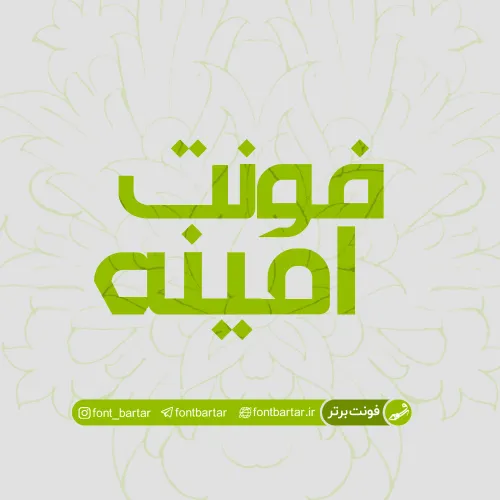
فونت فارسی امینه
در این پست از فونت برتر یک فونت دیگر با نام امینه را برای شما عزیزان آماده کرده ایم. فونت فارسی امینه از سری فونت های A می باشد که می توانید از این فونت نیز در طراحی خود به ویژه طراحی های تبلیغاتی، ساخت بنر و … استفاده کنید.
فونت فارسی امینه مورد استفاده برای:
• طراحان وب سایت و گرافیست های خلاق می توانند از این مجموعه زیبا فونت در طراحی پروژه های تبلیغاتی و تجاری خود کمک بگیرند.